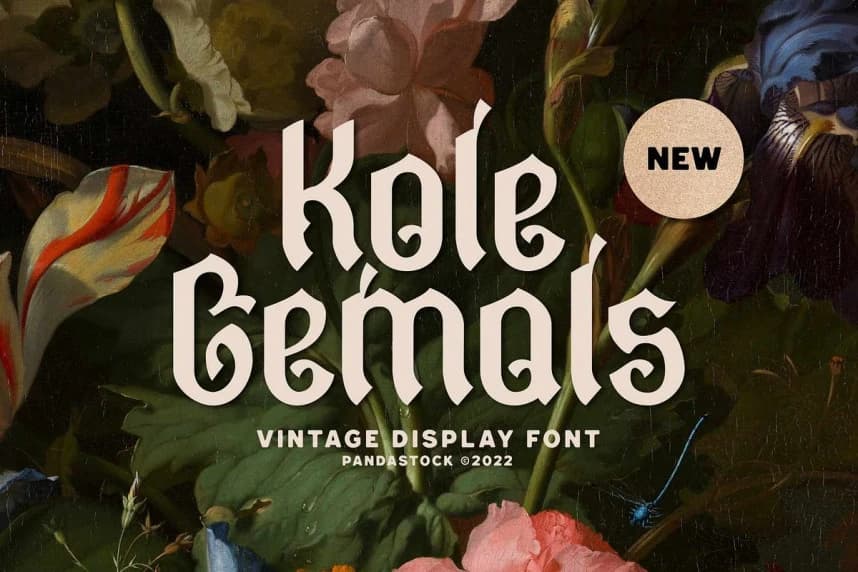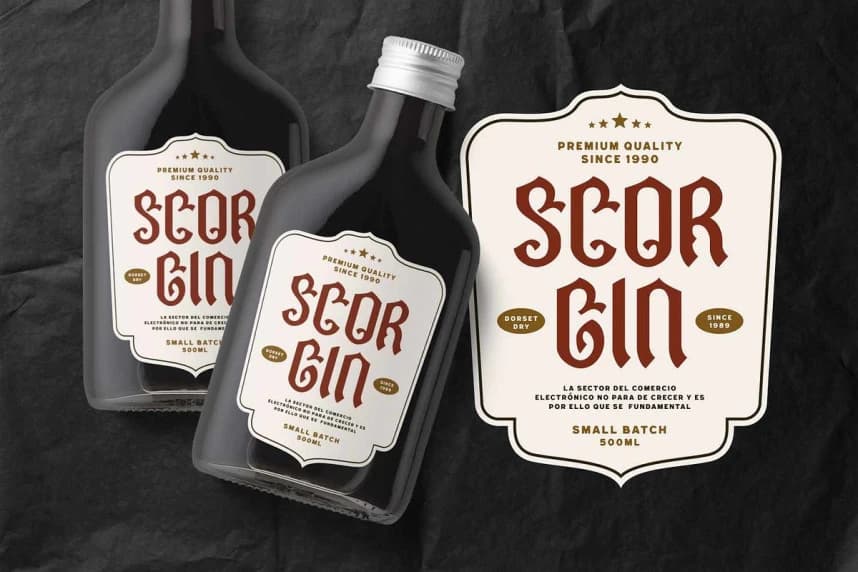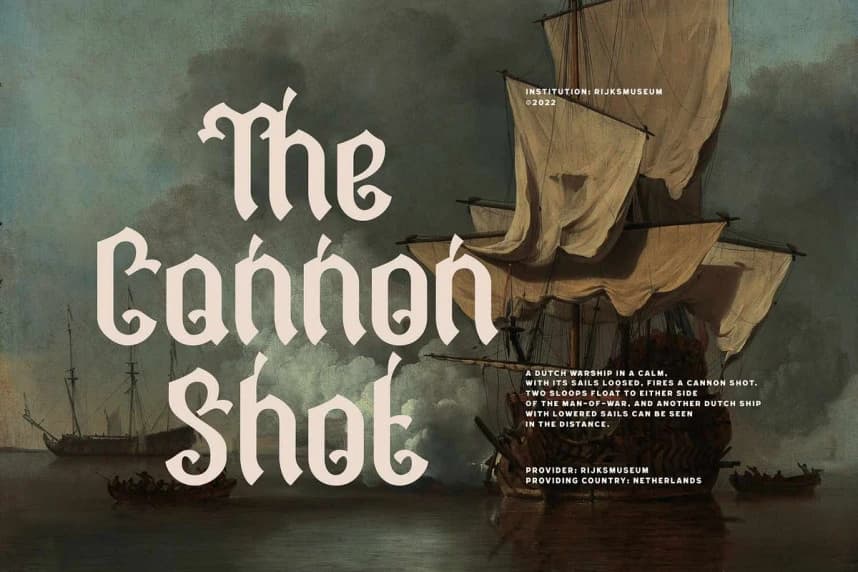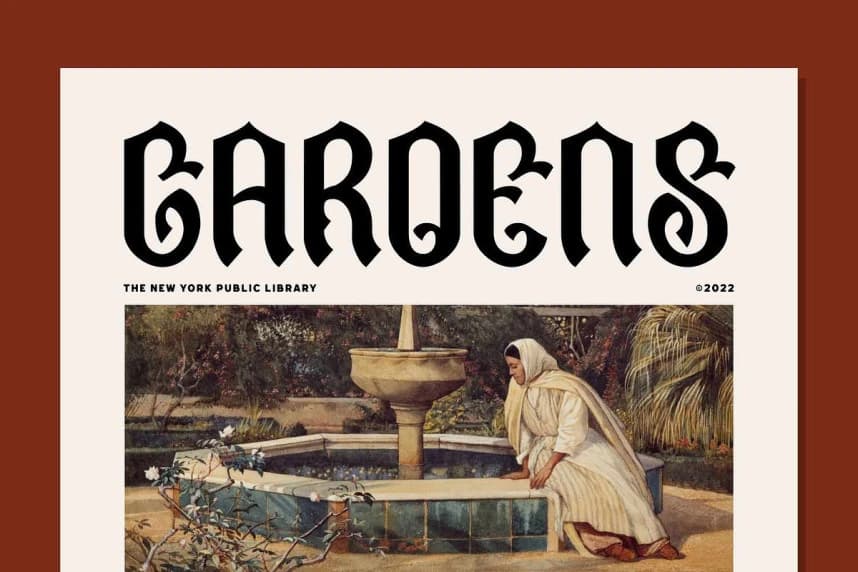
Kole Gemols Font
Kole Gemols fontu, geleneksel Blackletter'ın modern bir yorumu olup kalın ve köşeli harf biçimleri ile süslü dekoratif ayrıntılar içerir. Bu yazı tipi, tarihi Gotik stili çağdaş bir dokunuşla birleştirir; okunabilirliği artıran tutarlı çizgi kalınlığını sergilerken dr
Kole Gemols font, geleneksel Blackletter'ın modern bir yorumu olup, kalın ve köşeli harf biçimlerinin yanı sıra süslü dekoratif ayrıntılar sunar. Bu font, tarihsel Gotik stilini çağdaş bir dokunuşla birleştirir, tutarlı çizgi kalınlığını sergileyerek okunabilirliği artırır ve ortaçağ yazısının dramatik hissini korur.